ここ最近、
改めて明朝体の美しさに気づきました、私です(・ω・)ノシ
さて、「明朝体」とはどんなイメージをお持ちですか?
堅苦しい?
年寄り臭い?
いえいえ、そんなことないのです!
今回は明朝体の魅力を伝えるべく、きれいで美しい明朝体フォントをまとめてみました。
それでは、どうぞ!!
柔らかく優しい雰囲気のある明朝体ですね!
堅苦しくならず、気軽に使えそうです。
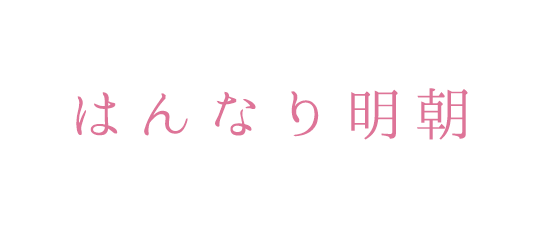
確かに、はんなり!
丸みのあるひらがなが可愛らしいです(´艸`*)
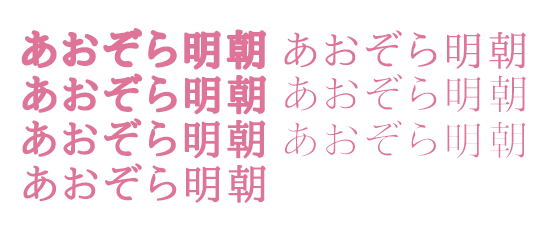
7種類のウェイト(文字の太さ)があり、
使用できる文字数が多いのも魅力的ですね。
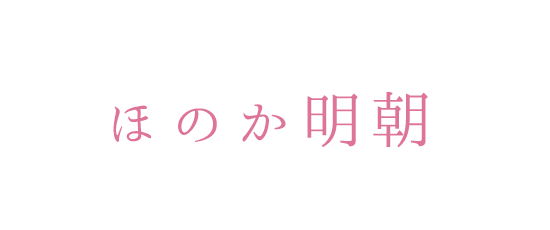
綺麗なラインの爽やかなフォントです。
青春のイメージ(´ω`*)
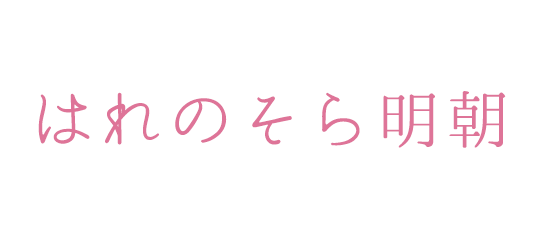
こちらも、涼しげなフォントに見えます。
ひらがなに、繋がっている部分があるのが特徴的。
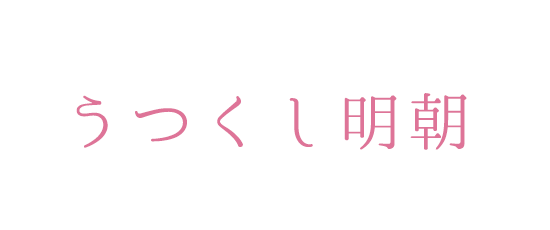
おぉ、なるほど美しい!
「て」がくるんッとなっていたり、ひとつひとつのこだわりを感じます。
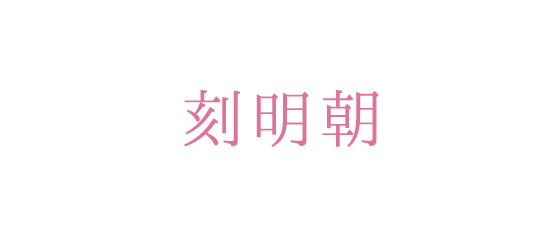
漢字に対してひらがなとカタカナが小さくなっています。
バランスがよく、見やすいフォントですね。
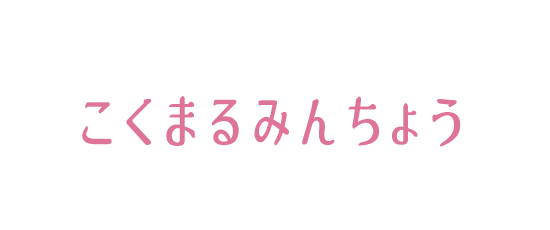
刻明朝よりも丸みがあり太くなっていて、
可愛らしい雰囲気があります。
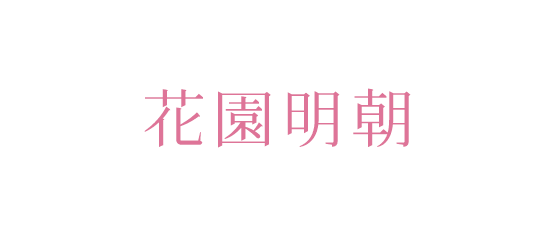
何よりも、多くの漢字が収録されているので
使いやすいフォントですね(*’ω’*)
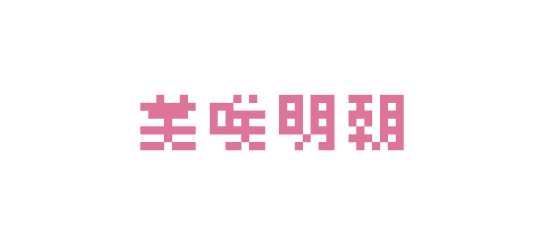
昔のゲームのようなドットのフォント。
涼しげな表現に「明朝体」が使えるというのは、これからの時期の制作に役立ちそうですね(*^^*)